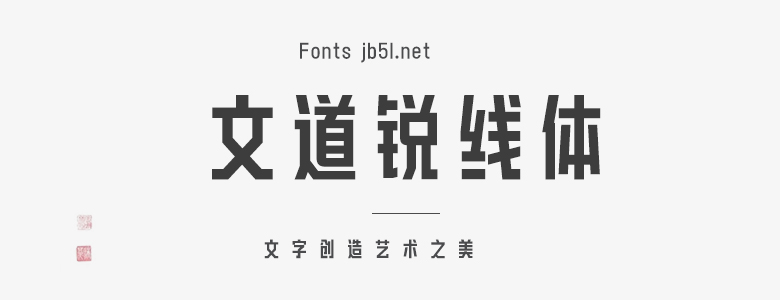
文道銳線體是一種獨(dú)具特色的字體,其設(shè)計(jì)理念是將傳統(tǒng)書法藝術(shù)的韻味與現(xiàn)代設(shè)計(jì)美學(xué)相結(jié)合。該字體線條流暢,轉(zhuǎn)折處呈現(xiàn)出銳利的角度,使得字體看起來既具有力量感又不失優(yōu)雅。 文道銳線體的字母比例勻稱,字形舒展,視覺效果十分舒適。字體中的字母線條精細(xì),筆畫的粗細(xì)處理得當(dāng),呈現(xiàn)出一種高級的質(zhì)感。此外,該字體的排版效果也非常出色,無論是在大段文字還是短句中,都能展現(xiàn)出良好的可讀性和美觀度。 總體來說,文道銳線體是一款極具美觀性和實(shí)用性的字體,適合應(yīng)用于各種設(shè)計(jì)場合,無論是報(bào)刊雜志、書籍封面還是品牌形象設(shè)計(jì),都能展現(xiàn)出其獨(dú)特的魅力。